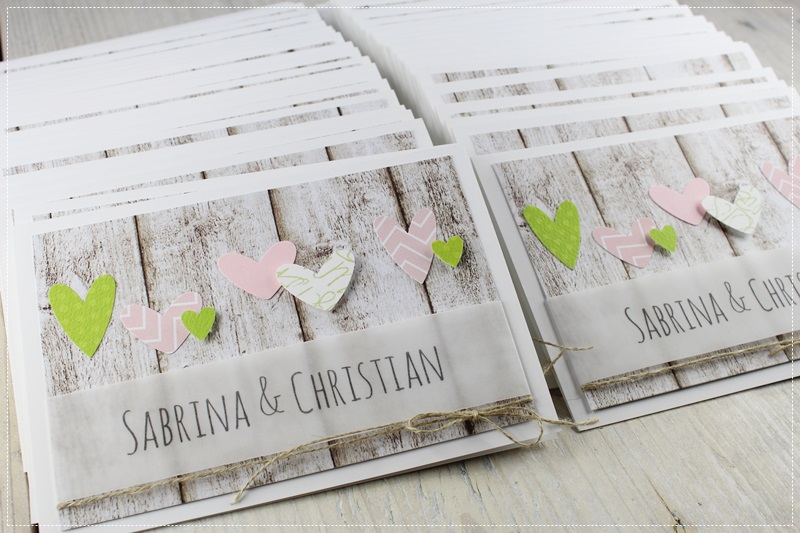
Hohe, schmale Schrift
Ich bin (neben all dem Weihnachtsstress - doch wer hat den nicht?!) gerade dabei mit meiner Verlobten unsere Hochzeits-Einladungskarte zu gestalten und noch auf der Suche nach einer Schrift für unseren Namen...
Auf der Suche nach Inspiration sind wir unter anderem auf folgende Karte gestoßen, deren Schriftart genau nach unserem Geschmack ist:
Erkennt von euch zufällig jemand diese Schriftart wieder? Oder kennt eine ähnliche, hohe, schmale Schriftart die wir verwenden könnten?